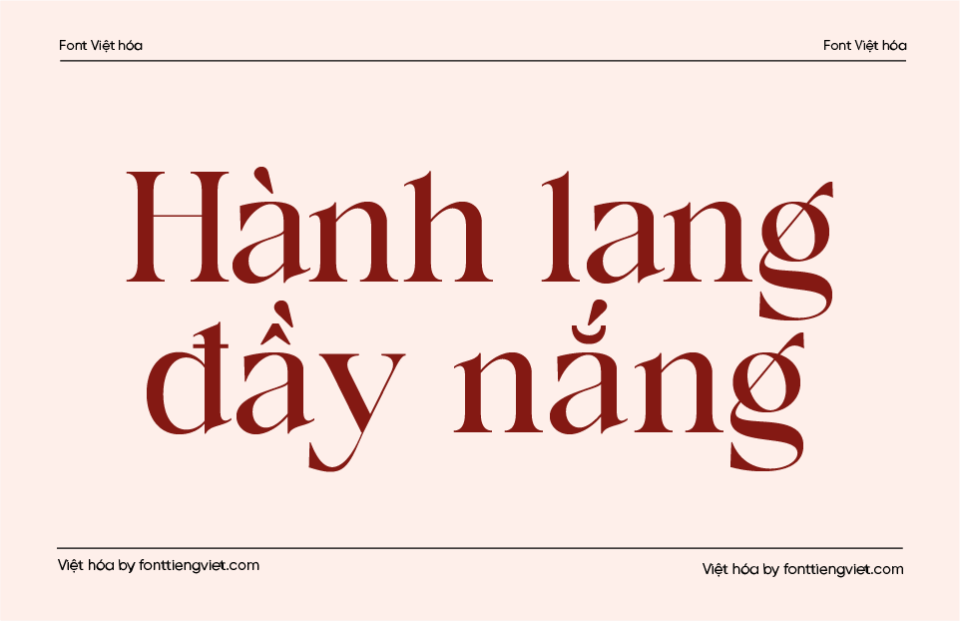
Font Việt hóa 1FTV VIP Leostut – Sang Trọng & Mạnh Mẽ Cho Thiết Kế Làm Đẹp
Giới thiệu về Font Việt hóa 1FTV VIP Leostut – Sang Trọng & Mạnh Mẽ Cho Thiết Kế Làm Đẹp
Trong thế giới đồ họa hiện đại, việc lựa chọn bộ Font Miễn Phí chất lượng đóng vai trò quyết định đến sự thành công của một bản thiết kế. Font Việt hóa 1FTV VIP Leostut – Sang Trọng & Mạnh Mẽ Cho Thiết Kế Làm Đẹp là một siêu phẩm typo được thiết kế đặc biệt nhằm tôn vinh vẻ đẹp đẳng cấp và cá tính. Với các đường nét được trau chuốt tỉ mỉ, bộ phông chữ này không chỉ giúp nội dung trở nên dễ đọc mà còn tạo ra một ấn tượng thị giác mạnh mẽ ngay từ cái nhìn đầu tiên. Đối với các bạn học sinh, sinh viên ngành mỹ thuật hay các nhà thiết kế trẻ, đây là công cụ hỗ trợ đắc lực để biến ý tưởng sáng tạo thành những sản phẩm chuyên nghiệp mang tầm quốc tế.
Những đặc điểm nổi bật của Font Việt hóa 1FTV VIP Leostut
Thiết kế hiện đại và tinh tế
Font Việt hóa 1FTV VIP Leostut sở hữu cấu trúc hình học cân đối, kết hợp giữa những nét thanh mảnh và những góc cạnh dứt khoát. Sự tương phản này tạo nên một diện mạo vừa thanh lịch, vừa quyền lực, rất phù hợp cho các dự án đòi hỏi tính thẩm mỹ cao. Các ký tự tiếng Việt được xử lý dấu một cách thông minh, không gây cảm giác rối mắt hay lệch tông so với các ký tự Latinh nguyên bản.
Khả năng ứng dụng đa dạng
Dù bạn đang thực hiện thiết kế logo cho một spa cao cấp, làm banner quảng cáo mỹ phẩm hay trình bày slide thuyết trình tại trường học, bộ phông này đều đáp ứng hoàn hảo. Độ dày của các nét chữ giúp nó hiển thị rõ nét trên cả màn hình kỹ thuật số lẫn ấn phẩm in ấn. Đặc biệt, phong cách của nó cực kỳ ăn ý với các tông màu tối giản như vàng kim, đen huyền bí hoặc trắng sứ.
Tại sao nên dùng Font Việt hóa 1FTV VIP Leostut – Sang Trọng & Mạnh Mẽ Cho Thiết Kế Làm Đẹp
Tối ưu hóa cho ngành công nghiệp làm đẹp
Ngành làm đẹp luôn yêu cầu sự chỉn chu và khắt khe về mặt hình ảnh. Font Việt hóa 1FTV VIP Leostut – Sang Trọng & Mạnh Mẽ Cho Thiết Kế Làm Đẹp mang lại cảm giác tin cậy và sự chuyên nghiệp tuyệt đối. Khi sử dụng bộ chữ này, các thương hiệu có thể dễ dàng truyền tải thông điệp về sự xa xỉ và chất lượng dịch vụ đến khách hàng một cách tự nhiên nhất.
Tiết kiệm thời gian chỉnh sửa
Việc sử dụng một bộ phông đã được Việt hóa hoàn chỉnh giúp người dùng tránh được các lỗi hiển thị phổ biến như lỗi font, mất dấu hay khoảng cách chữ không đều. Điều này rất quan trọng đối với các bạn học sinh khi làm bài tập lớn hoặc các nhà thiết kế cần hoàn thiện dự án đúng tiến độ mà vẫn đảm bảo được tính nghệ thuật cao nhất.
Kết luận và trải nghiệm thực tế
Việc sở hữu bộ Font Việt hóa 1FTV VIP Leostut – Sang Trọng & Mạnh Mẽ Cho Thiết Kế Làm Đẹp trong bộ sưu tập cá nhân sẽ mở ra nhiều cơ hội sáng tạo không giới hạn. Đây không chỉ là một công cụ chữ viết thông thường mà còn là nguồn cảm hứng để tạo nên những tác phẩm nghệ thuật có chiều sâu. Hãy bắt đầu nâng tầm dự án của bạn ngay hôm nay bằng cách tải về và sử dụng các bộ Font Miễn Phí, Font Việt Hóa, Font Việt hóa 1FTV VIP Leostut – Sang Trọng & Mạnh Mẽ Cho Thiết Kế Làm Đẹp để cảm nhận sự khác biệt vượt trội mà chúng mang lại cho không gian thiết kế của bạn.